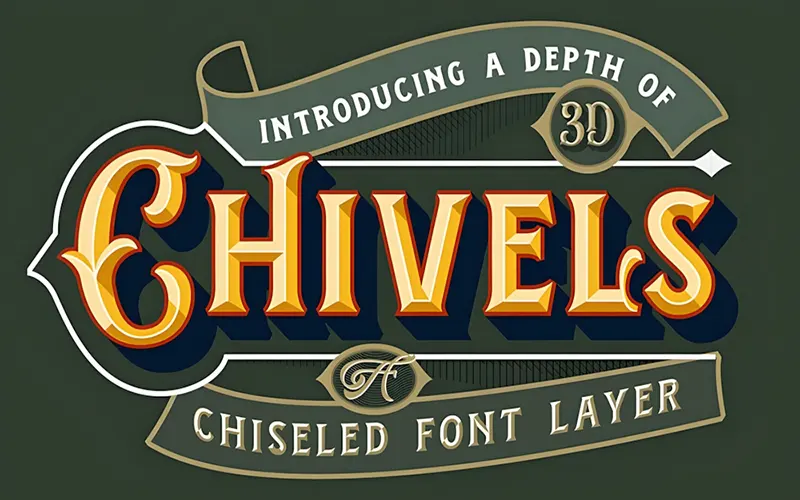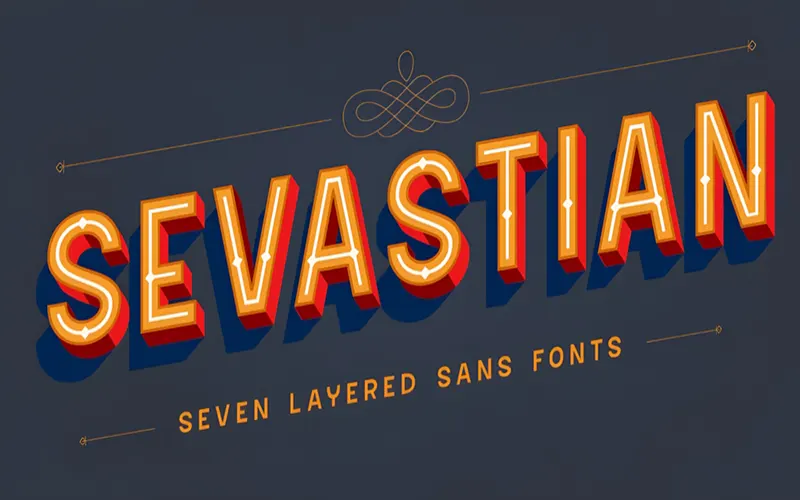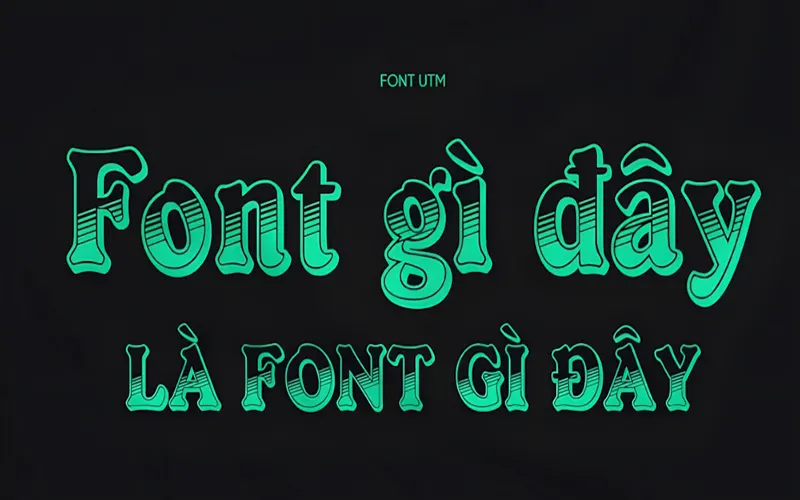
Tổng hợp 55 Font 3D đẹp dành cho thiết kế
Font 3D là kiểu chữ được thiết kế với hiệu ứng ba chiều, tạo cảm giác chiều sâu, khối nổi và không gian. Nhờ hiệu ứng thị giác đặc biệt, font 3D mang lại sự sống động và cuốn hút, giúp chữ cái không còn đơn điệu mà trở nên sinh động và có “trọng lượng” trong mắt người xem.
Đặc điểm nổi bật của Font 3D
• Hiệu ứng chiều sâu: Các ký tự thường được tạo bóng, phối màu hoặc chồng lớp để tạo ảo giác ba chiều, khiến chữ như “nhảy” ra khỏi nền.
• Đa dạng phong cách: Font 3D có thể mang hơi hướng hiện đại, hoạt hình, retro hoặc thậm chí giả kim loại, nhựa, thủy tinh… phù hợp nhiều mục đích thiết kế khác nhau.
• Tạo điểm nhấn mạnh: Font này thường được sử dụng cho tiêu đề, dòng chữ cần nhấn mạnh vì dễ thu hút ánh nhìn và tạo cảm giác chuyên nghiệp, sáng tạo.
Ứng dụng của Font 3D
• Thiết kế tiêu đề, poster quảng cáo: Font 3D giúp tiêu đề nổi bật hơn trên nền phẳng, dễ dàng tạo ấn tượng đầu tiên với người xem trong các chiến dịch marketing, quảng bá sản phẩm hoặc sự kiện.
• Bìa sách, bìa tạp chí, trang bìa slide: Với cảm giác bắt mắt và có chiều sâu, font 3D thường được dùng ở những vị trí quan trọng trong các ấn phẩm in hoặc kỹ thuật số.
• Logo và nhận diện thương hiệu: Một số thương hiệu chọn font 3D để thể hiện cá tính mạnh, năng động hoặc phong cách sáng tạo – đặc biệt là trong ngành game, giải trí, công nghệ.
• Thiết kế dành cho trẻ em hoặc hoạt hình: Với phong cách đáng yêu, vui nhộn, các font 3D hoạt hình rất phù hợp trong sách thiếu nhi, poster phim hoạt hình, trò chơi hoặc bao bì sản phẩm cho trẻ em.
• Thiết kế mạng xã hội, YouTube thumbnail, intro video: Những dòng chữ 3D bắt mắt giúp thu hút người xem ngay từ cái nhìn đầu tiên, đặc biệt là trong môi trường truyền thông số nhiều cạnh tranh.
Font 3D không chỉ là một lựa chọn về mặt thẩm mỹ mà còn là công cụ mạnh mẽ để tạo ra ấn tượng thị giác mạnh mẽ trong thiết kế. Nhờ sự đa dạng về kiểu dáng và khả năng nổi bật, font 3D là lựa chọn lý tưởng cho mọi nhà thiết kế muốn tạo sự khác biệt cho sản phẩm của mình.